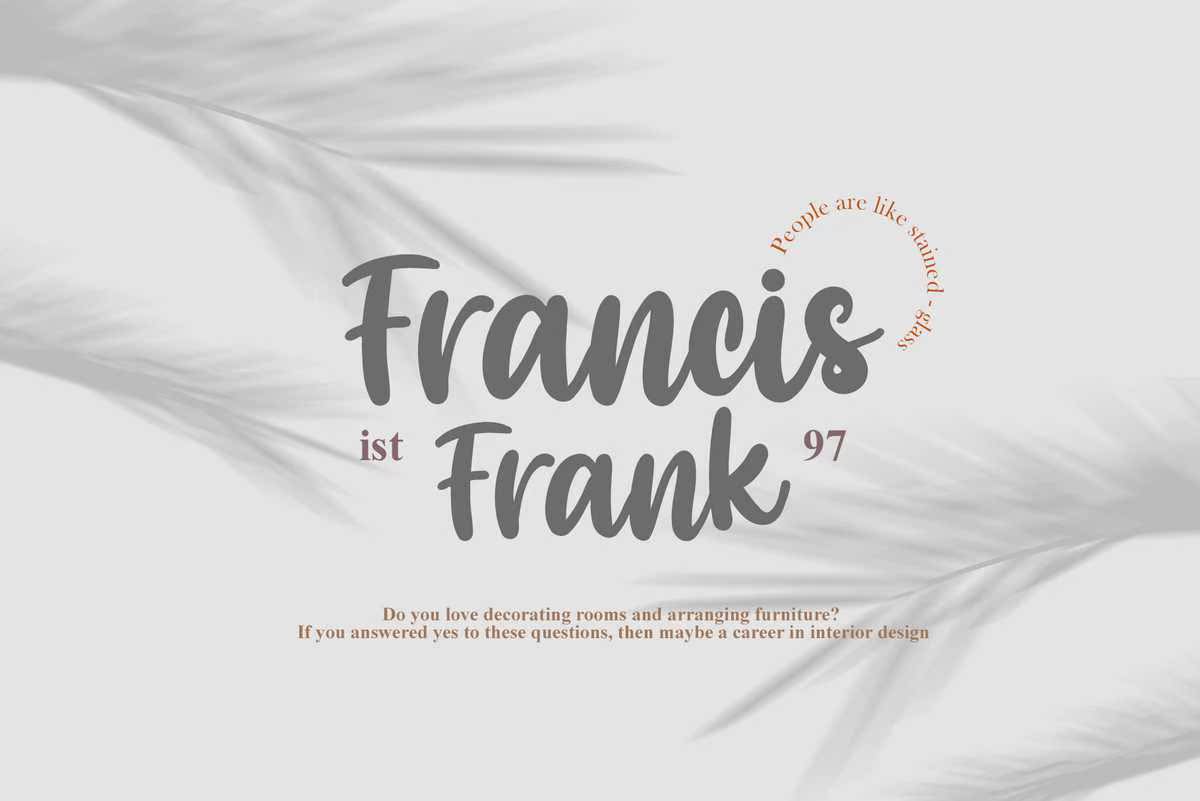
AngelicaCaroline手写字体。适合您项目的文字和数字集合非常适合于标识、品牌设计、标识设计、数字刻字艺术、T恤/服装、海报、杂志、标志、广告设计和任何设计需求。AngelicaCaroline手写字体。适合您项目的文字和数字集合非常适合于标识、品牌设计,标志设计、数字文字艺术、T恤/服装、海报、杂志、标志、广告设计和任何设计需求。